日本語書体三傑の展開
和字書体、漢字書体との組み合わせを網羅することを考えて「日本語書体十二撰」を考えたのだが、それとは別に構想していたのが「日本語書体三傑」である。
和字書体としては、「和字おゝはなぶさ Family 7」(2009年)、「和字おゝくれたけ Family 9」(2009年)、「和字おゝことのは Family 9」(2012年)としてリリースした。これに漢字書体、欧字書体を組み合わせて、グランド・ファミリーとして構築しようと考えている。
さらに「おゝまどか」「おゝはるか」「おゝたまゆら」各ファミリー、「おゝはやと」「おゝくらもち」「おゝみなもと」各ファミリーへと夢は膨らんでいく。
漢字書体においては、明治時代に東京築地活版製造所が制作していた近代明朝体・呉竹体・安竹体の主要3書体が復刻されることになり、欣喜堂としての第2の柱となりうるものだと考えている。
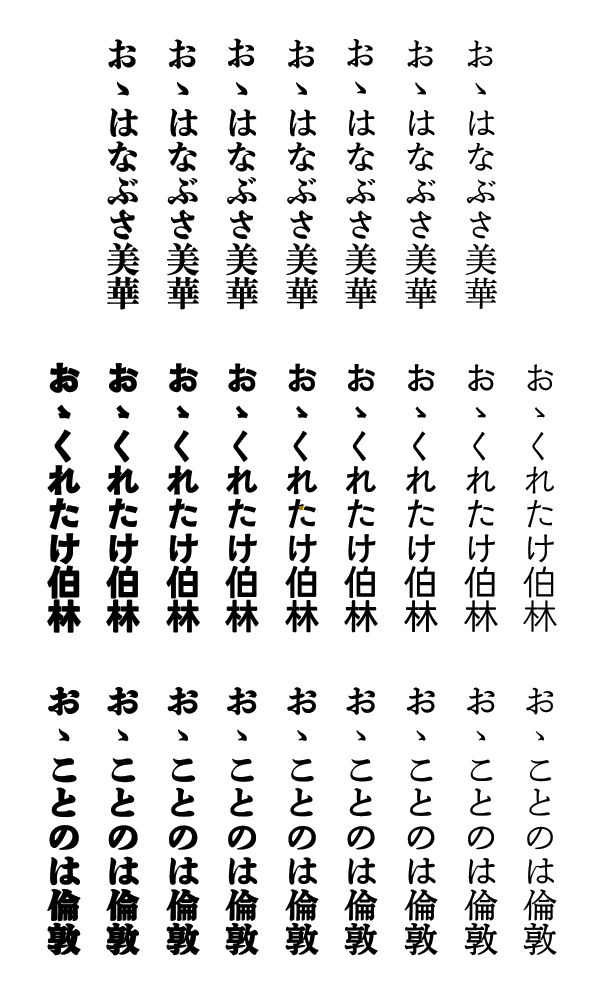
[展開案]
「KOおゝはなぶさ美華」ファミリー
「KOおゝくれたけ伯林」ファミリー
「KOおゝことのは倫敦」ファミリー
「KOおゝまどか美華」ファミリー
「KOおゝはるか伯林」ファミリー
「KOおゝたまゆら倫敦」ファミリー
「KOおゝはやと美華」ファミリー
「KOおゝくらもち伯林」ファミリー
「KOおゝみなもと倫敦」ファミリー